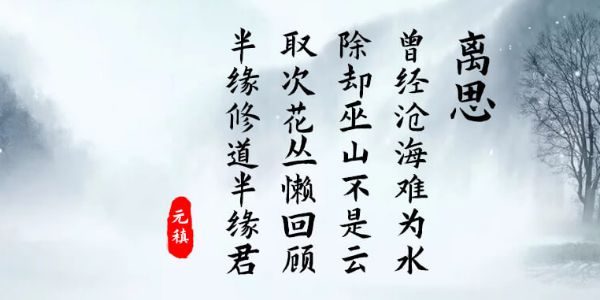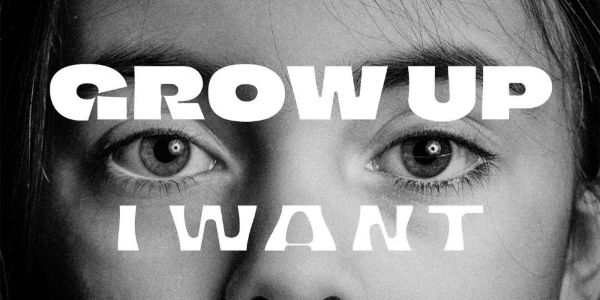
免费字体越来越多了,免费字体都开始内卷了?
听名字就很有科技含量,不过金山云技术体,也确实是金山云UED设计团队,历时四年发布的首款原创字体库,主打偏向年轻态、硬朗、具有活力的字体风格,允许任何个人和企业免费使用。
阿里妈妈数黑体是阿里妈妈·智造字打造的第一款AI字体,其字型饱满而简练,先锋又中正 ,适合多种使用场景,对全社会免费开放。
鸿雷板书简体都用过吧,这不设计师又带着它的第二款全渠道免费商用字,跟大家见面了,依然是手写字,依然是高质量!(听说鸿雷想通过两年的时间,看看自己的字迹有没有进步,你们觉得呢?)发布免费字体是菩萨行为,大家都很感激。作为一名专业的设计师,不光要学会薅羊毛,更要薅有品质的羊毛,下面这些长年霸屏+即将霸屏的免费商用字,你都用过吗?
虽然推这款字体属于是王婆卖瓜自卖自夸,但是字由芳华体,它!真!的!值!得!设计师参考了大量的老上海美术字,并以此为灵感,延伸成字库,还一举夺得2018年日本字体年鉴学生组最佳奖,是一款非常有特色的字体(放眼往去,它就是免费字体中的一枝独秀)。
既有芳华体,怎能没有它的另一半文艺黑,在字由上已经有687万次的应用,堪称免费字的尊上。它好用就好用在既有黑体的醒目感,又有图形设计的艺术感,用在任何场景,都嘎嘎好看!
江西拙楷这款字刚出的时候,可能设计师黄煜臣都没想到能这么火,但它就是能驾驭一切场景,尤其是字型中那种自然的斑驳肌理,给人天然的亲近感,简直就是百搭之王。
这款字体才上线不久,但柚子可以大胆预测,它即将爆火,因为它既有力量感,可以稳稳地当标题字,同时又运用了逆反差风格,让人非常有记忆点,很难想象是一款免费字体,用到的人都有福了。今天的免费套餐你还满意吗?还有更多优质的免费字,尽在字由客户端~